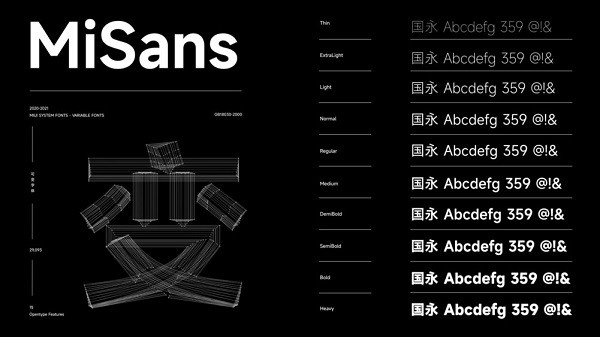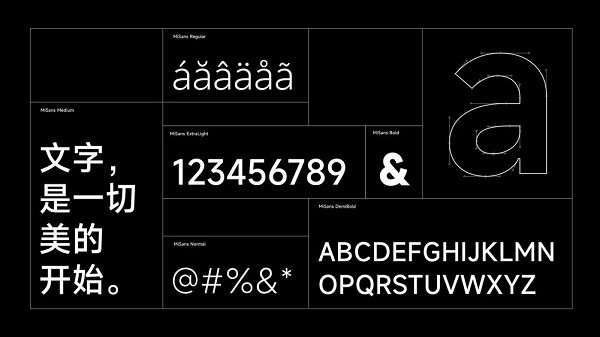
MIUI 13 采用全新系統(tǒng)字體 MiSans;筆型平直有力,設(shè)計(jì)更加簡(jiǎn)約,減少視覺負(fù)擔(dān),更有利于屏幕顯示。共包含29,093個(gè)字符,支持多種語(yǔ)言。MiSans 提供了多種 OpenType 功能,可根據(jù)特定需求來(lái)選擇不同形態(tài)的字符,例如某些標(biāo)點(diǎn)符號(hào)可以根據(jù)周圍字母的形態(tài)自動(dòng)調(diào)整至合適的位置。MiSans字重齊全,層級(jí)清晰,10個(gè)字重全部開放下載,供全社會(huì)免費(fèi)商用。
font-feature 屬于 Opentype 中的高級(jí)排版功能,也就是可以讓字體排版更加精致,符合實(shí)際設(shè)計(jì)、開發(fā)需求,可根據(jù)特定設(shè)計(jì)需求選擇不同的字體形態(tài)。大部分軟件都可以通過 Opentype 面板訪問此功能。(部分特性在MIUI系統(tǒng)應(yīng)用中不會(huì)默認(rèn)生效)